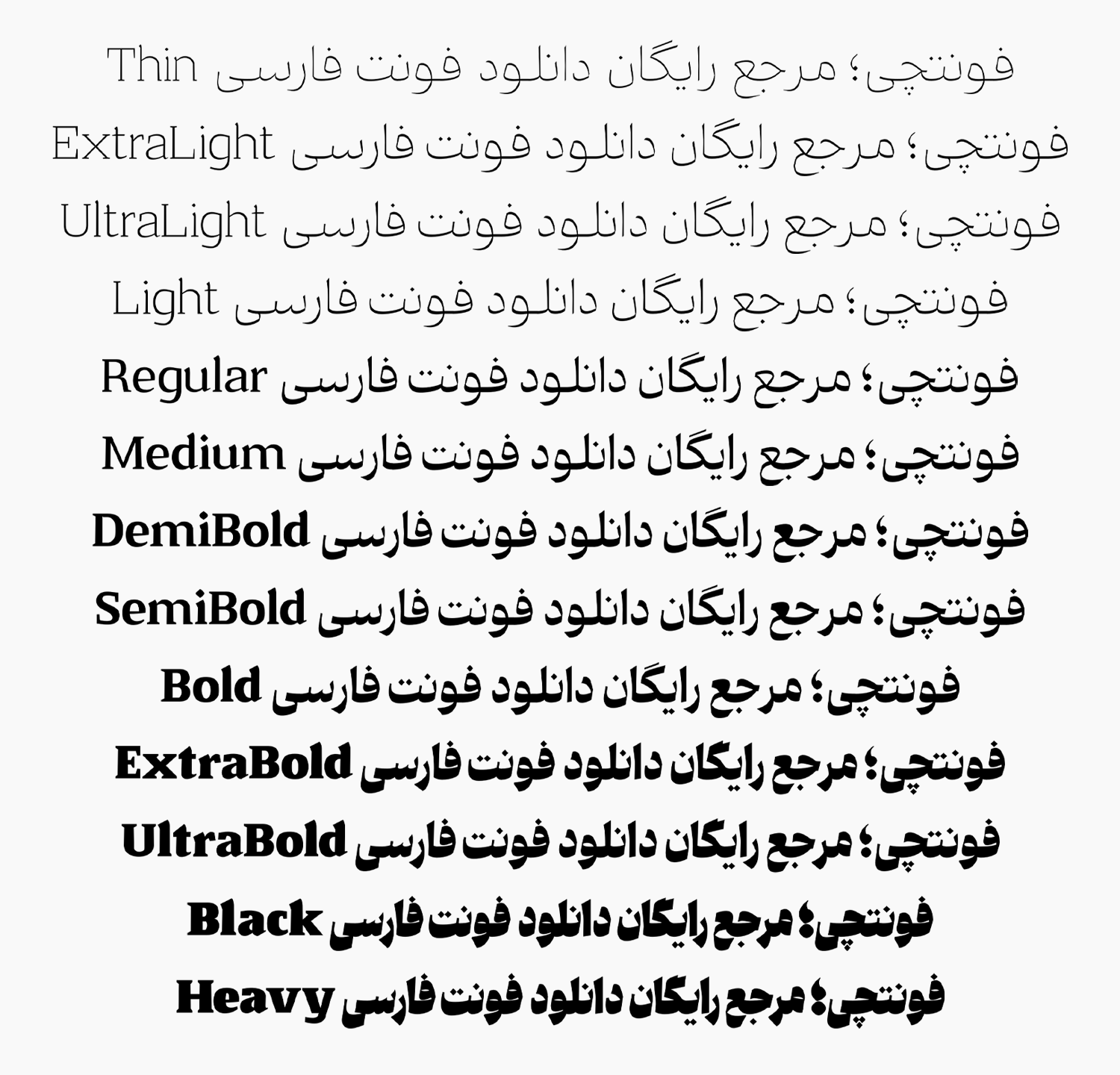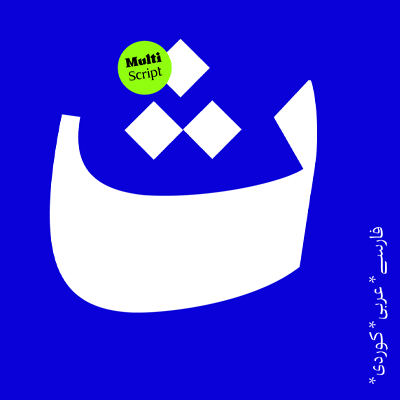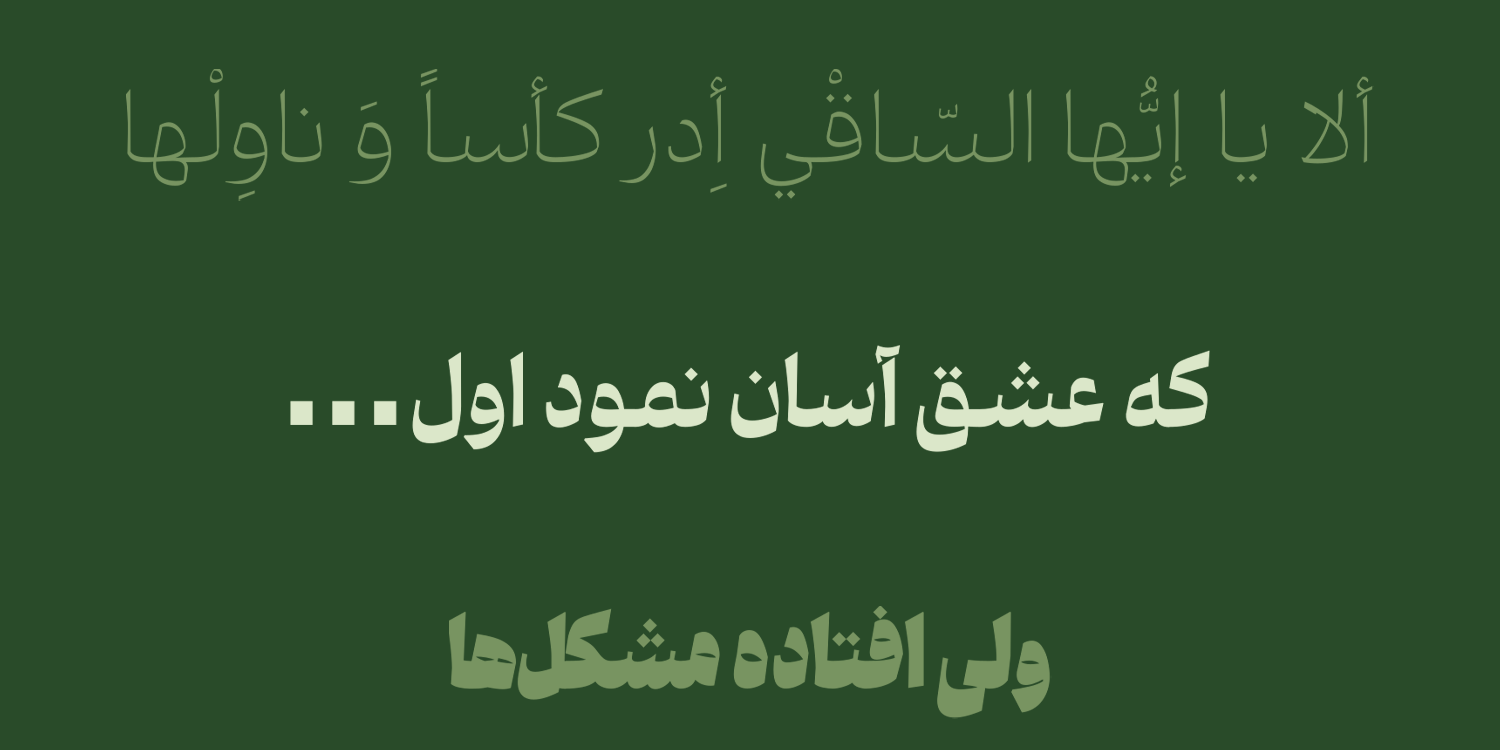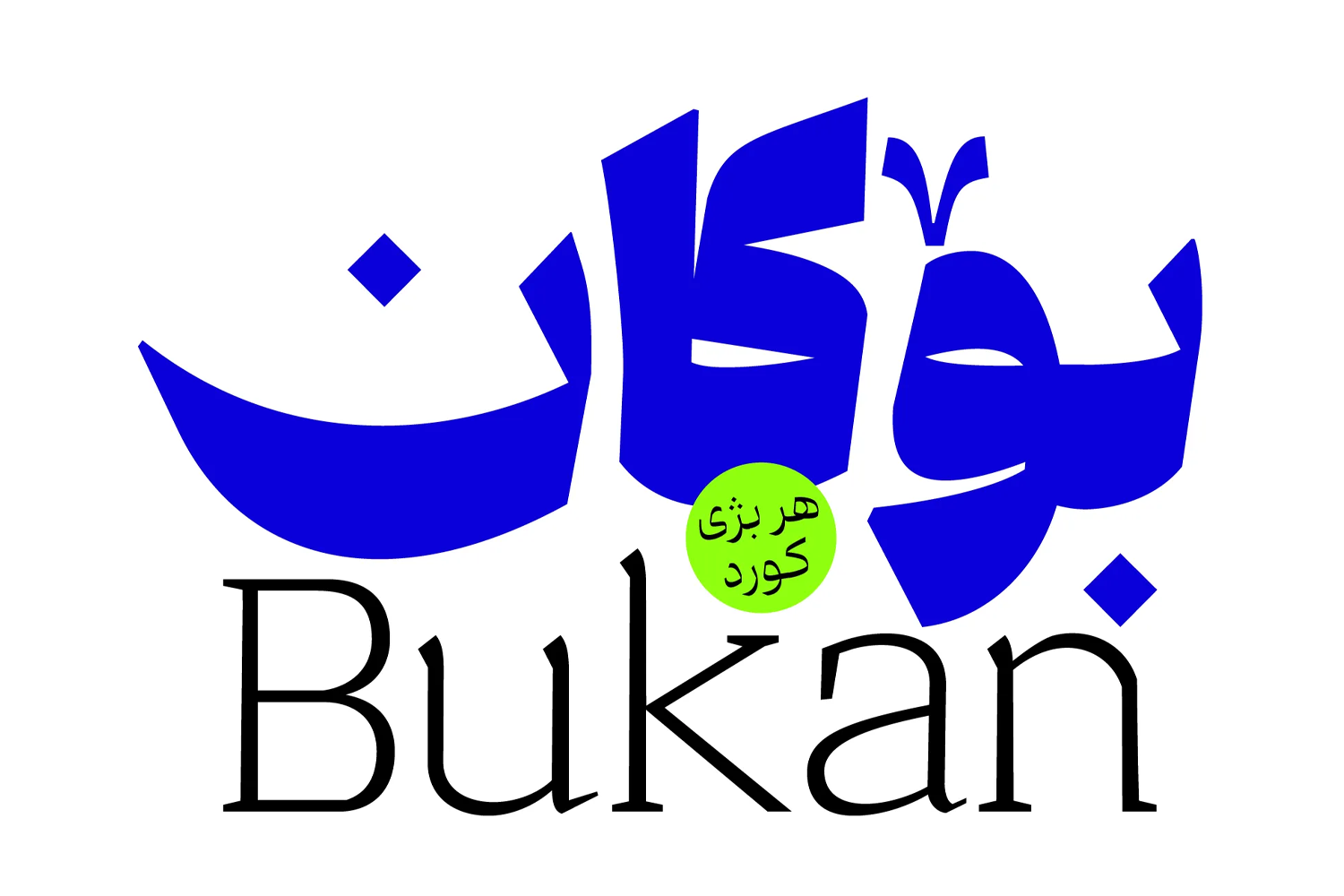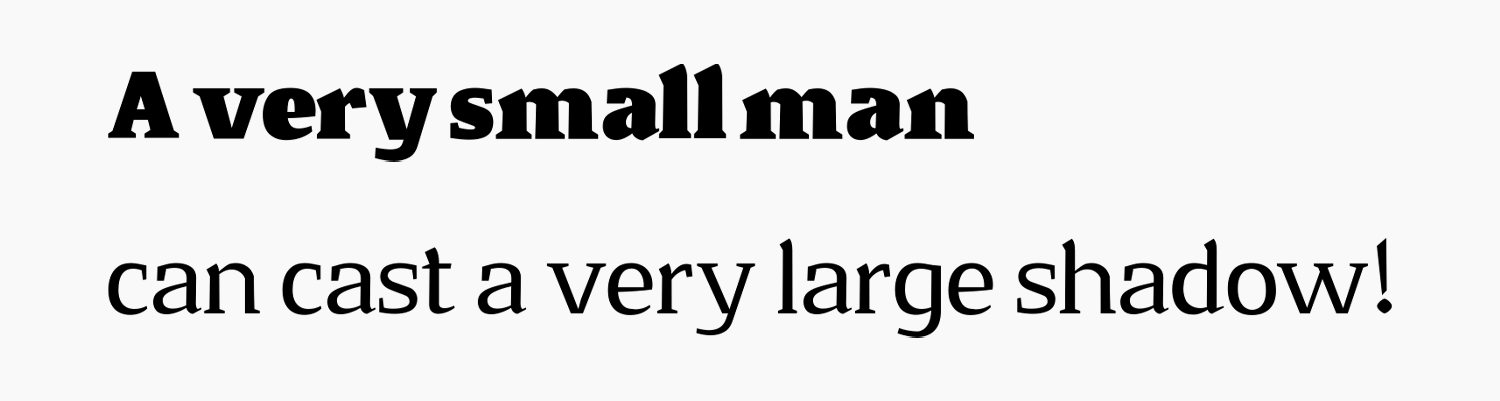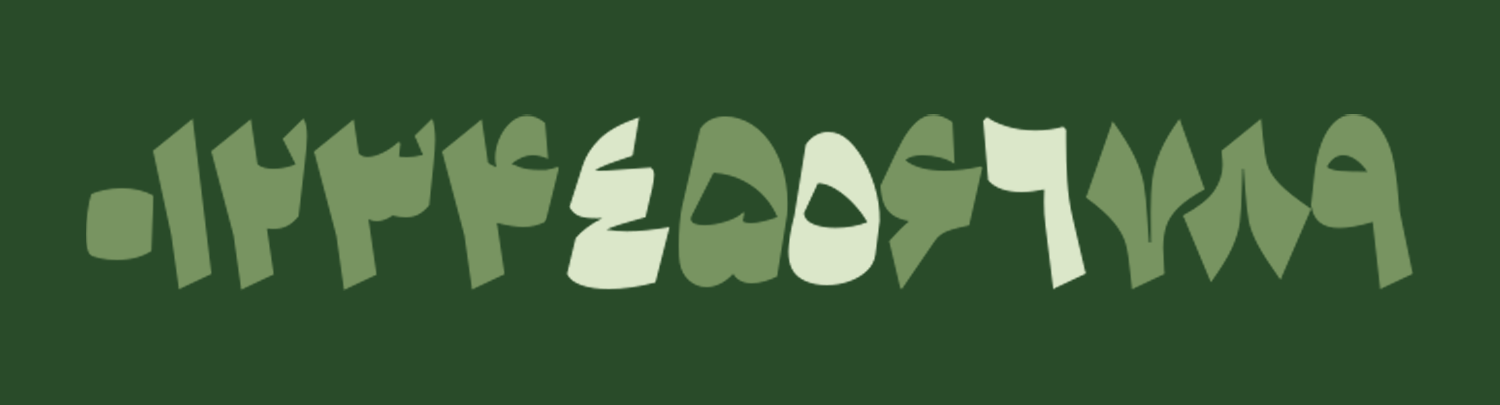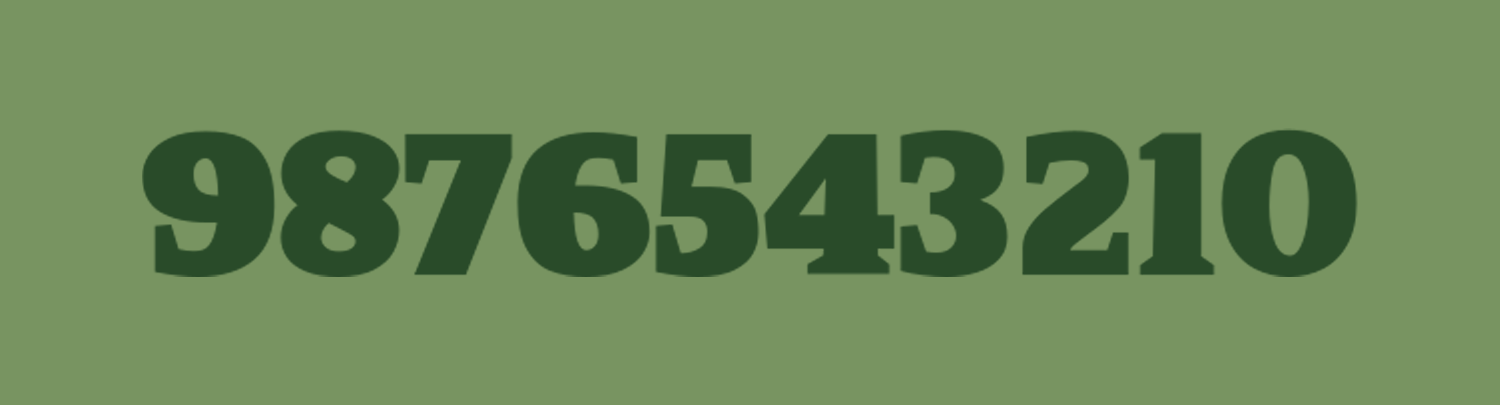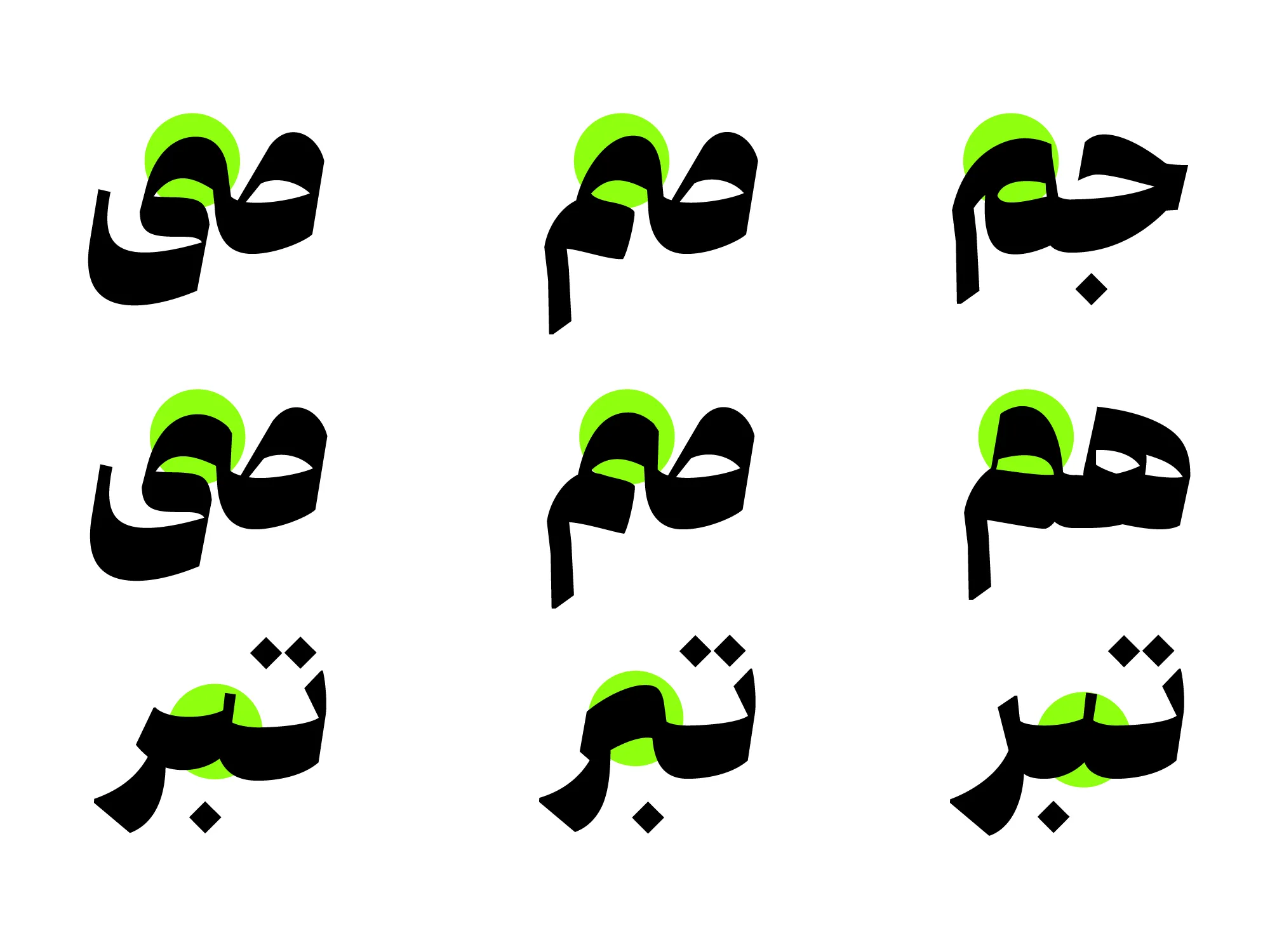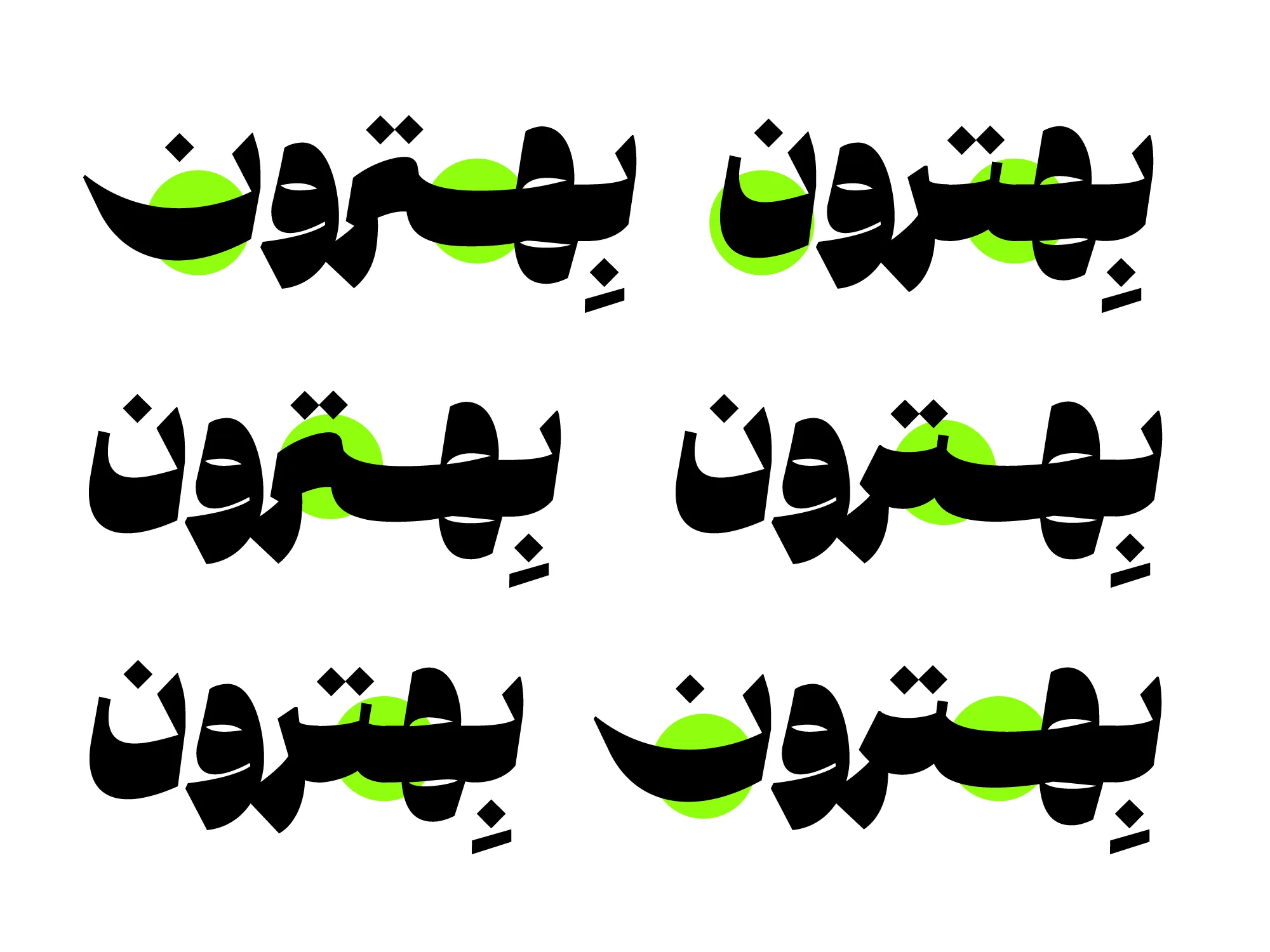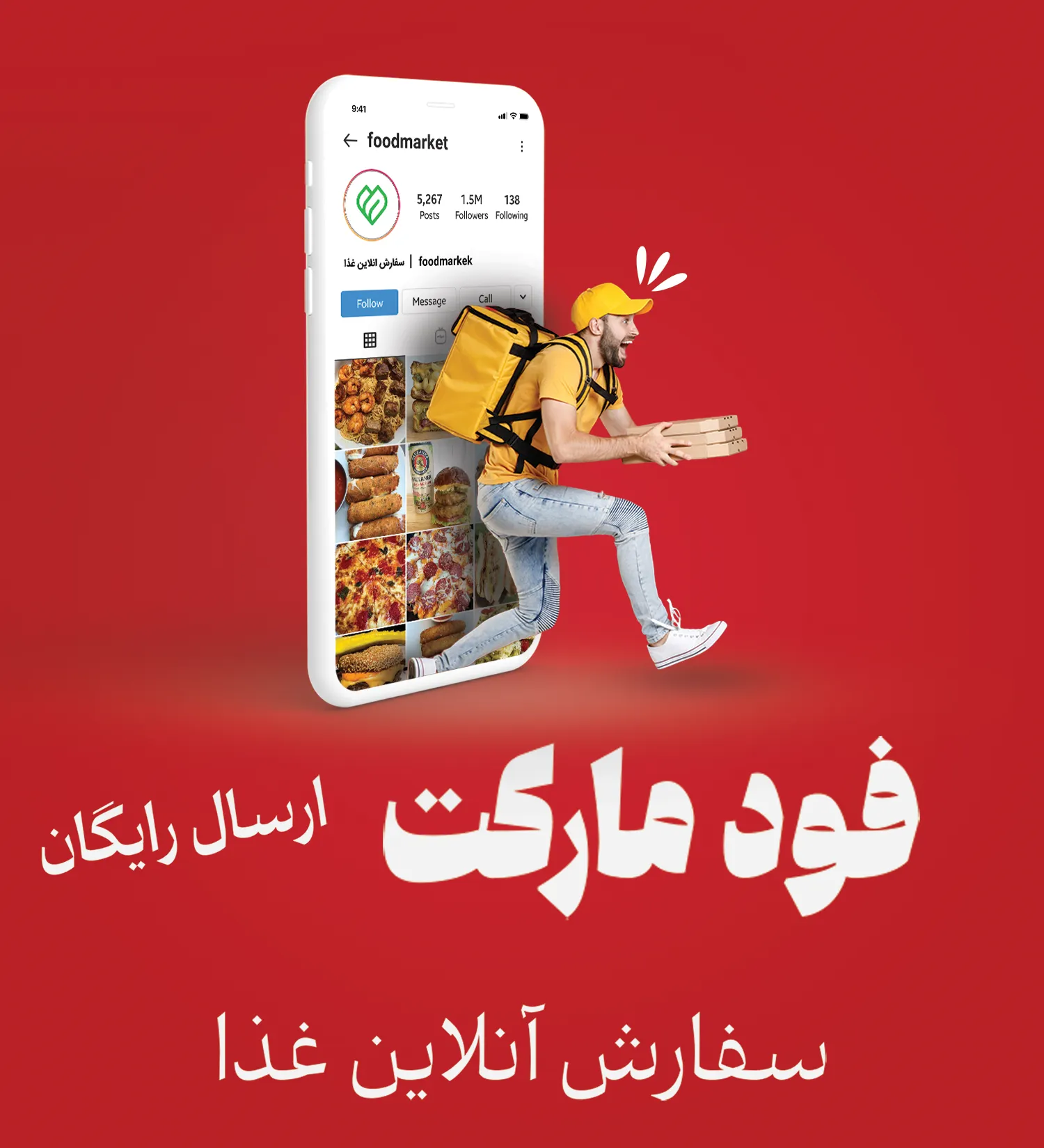
فونت ونوو (Veno)
فونت ونوو (به انگلیسی: Veno) یک فونت جدید و دارای ۱۳ وزن مختلف است که با سبک نسخ امروزی به شیوه معاصر طراحی شده و با توجه به تنوع بالایی که از نظر وزنی و امکانات خاص دارد برای استفاده در عناوین و تبلیغات مناسب است. فونت ونوو رایگان نیست و در ۳ بسته قابل خریداری است.
این قلم توسط امیر مصباحی طراحی شده است که پیش از این چندین فونت مختلف از وی را مورد بررسی قرار دادهایم. از این فونت میتوانید جدای از بحث عناوین، در محیط وب و دیجیتال به منظور فونت سایت و همچنین فونت مطبوعات چه برای نشریههای آنلاین و چه فضای چاپی روزنامه و مجلات استفاده کنید که نگاه مخاطب را با توجه به ساختار طراحی و وزنی به خود جذب خواهد کرد.
در ادامه این نوشته از سایت فونتچی به نقد و بررسی فونت ونوو خواهیم پرداخت؛ قلمی خانوادهدار که ۱۳ وزن مختلف نازک تا سنگین را در خود داشته و جلوه ویژه متفاوتی را از خط نسخ به نمایش میگذارد.
بررسی و دانلود فونت ونوو (Veno)
فونت Veno قلمی با وزن متنوع و صد البته سیاه است که مشابه با برخی فونتهای خاص فارسی، عاملی که بین ضخامت حروف نسبت به ساختار فرمها ایجاد شده، به آن ساختاری جذاب و در عینحال مدرن بخشیده است.
در ابتدا، هدف اصلی از طراحی فونت ونوو، تولید یک تایپفیس تنوعبخش در یک وزن سنگین بود. اما در طول فرآیند طراحی، با در نظر گرفتن قابلیتهای فرمی، به یک خانواده مدرن گسترش یافت تا بتواند نیازهای مختلف را برآورده کند.
امیر مصباحی؛ طراح فونت ونوو.
وزنهای ضخیم و سنگین این فونت کنتراست ضخامت بیشتری دارند که در بخشهایی همچون تیترها، عناوین و نقلقولها در طراحی صفحات وب زندگی میبخشند و بافتی متفاوت و برجسته را بهوجود میآورد.
سبک طراحی و وزن فونت ونوو
فونت ونوو در ۱۳ وزن مختلف به سبک نسخ امروزی و معاصر طراحی شده است. با سبک طراحی وزنی و چینشی که برای دندانهها، منحنی، چشمیها و خطوط برای حروف مختلف در نظر گرفته شده، کنتراست ضخامتی متفاوتی را با یک سبک ویژه و خاص در اختیار قرار میدهد که جلوهای عالی در متنهای کوتاه، خصوصا با اندازه فونت بزرگ و در وزنهای سنگین دارد.
در حالت کلی این خانواده فونت برای استفاده در عناوین که نیاز به فونتی پهن و در عینحال نمایشی داشته باشید گزینهای عالی خواهد بود. از دیگر نمونه قلمهایی با این سبک میتوان به فونت پیکان اشاره کرد.
پشتیبانی از ۴ زبان متنوع
با دانلود فونت فارسی ونوو علاوه بر اینکه به قلمی با تمامی حروف و گلیفهای فارسی دسترسی دارید، از زبانهای دیگری که مبتنی بر رسم خط فارسی هستند نیز پشتیبانی میکند. پشتیبانی این فونت در زبانهای خاورمیانهای طوری است که در هر زبان، تفاوت طراحی حروف بر اساس استاندارد یونیکد است.
به عنوان مثال در زبان عربی که حروفی مثل «ک، ی، ه، ؤ، ئ» دارای شکل متفاوتی از نظر فارسی بوده و همراه با کاراکترهای همزه یا دو نقطه هستند هریک گلیف خاص خود را دارند.
از نظر اعراب گذاری این زبان نیز همین مسئله رعایت شده و اعراب در همنشینی درستی بر روی حروف قرار دارند که موجب به هم چسبیدن یا به هم ریختگی متن نمیگردد.
زبان دیگری که این فونت به صورت ویژه روی آن متمرکز شده است، کوردی است. با توجه به اینکه در این زبان از کاراکترهای تزئینی بسیاری استفاده میشود و مشابه زبان عربی دارای حروفی است که از نظر این نوع نشانهگذاری دارای گلیف خاصی هستند، امکان استفاده حرفهای از این قلم را برای زبان کردی نیز در اختیار دارید.
این فونت از زبا انگلیسی نیز پشتیبانی کرده و حروف در این زبان نیز به شکلی که قلم با ساختار نسخ نمایان شود دارای طراحی اختصاصی هستند.
دارای اعداد عربی و فارسی حرفه ای هک شده
ویژگی دیگر فونت ونوو پشتیبانی حرفهای از اعداد است که در اینجا هم هر زبان دارای گلیف اختصاصی خود خواهد بود. حروفی که در هر سه زبان فارسی، عربی و انگلیسی شکل متفاوتی داشته یا بین دو زبان فارسی و عربی مشترک هستند دارای گلیف خاص خود بر مبنای زبان صفحه کلید هستند.
به عنوان نمونه اعداد «۴۵۶» در زبان عربی که دارای ظاهری متفاوت نسبت به اعداد فارسی «۴۵۶» هستند طراحی شدهاند.
در بسته دانلود فونت ونوو رایگان یک پوشه نیز مخصوص اعداد فارسی قرار گرفته شده است. این گروه از فونتها که به صورت اختصار با پسوند FD نامگذاری شدهاند، در آنها کلیه اعداد انگلیسی به جای اینکه دارای گلیف زبان انگلیسی برای نمایش اعداد باشند، دارای گلیف اعداد فارسی هستند. در نتیجه زبان صفحه کلید روی هر زبان غیرفارسی هم که باشد، در هر حالتی اعداد فارسی تایپ خواهند شد.
اعداد در زبان انگلیسی نیز متناسب با سبک نسخ فارسی طراحی شده است. همچنین درون بسته دانلود فونت Veno یک پوشه مخصوص هم چه از نظر اعداد و چه حروف فاقد گلیفهای لاتین در نظر گرفته شده است. اگر از این گروه فایل فونتها استفاده کنید، فاقد حروف و اعداد انگلیسی است که مناسب برای توسعه نرمافزاری خواهد بود.
پشتیبانی از ترکیبات و حروف جایگزین فونت ونوو
فونت ونو از نظر پشتیبانی حروف آلترنیتیو یا همان حروف جایگزین دارای ساختاری پیشرفته است. در این قلم خانوادهدار تمامی وزنهای قلم که شامل نسخه نازک تا سنگین میشود، بسیاری از حروف فارسی نظیر «ی، ن، م، ک، گ، ه» دارای چند حالت مختلف هستند که به زیبا سازی کلمات کمک میکند.
از طرفی دیگر برخی ترکیبات پر استفاده مانند «ـی، ـم، سی، شی، صی، ضی، ـن» نیز دارای چند حالت مختلف هستند که امکان تایپ متفاوت کلمات را میدهد.
این میزان تنوع از نظر حروف جایگزین در یک فونت که مختص کارهای گرافیکی و تبلیغاتی است، یک موضوع مهم است. چرا که کمک میکند با تایپ متفاوت بسیاری از کلمات کلیدی که تاثیر روانی خوبی روی نگاه مخاطب دارد، اثرپذیری بهتری چه از نظر تبلیغاتی و چه آگاهی از برند داشته باشد.